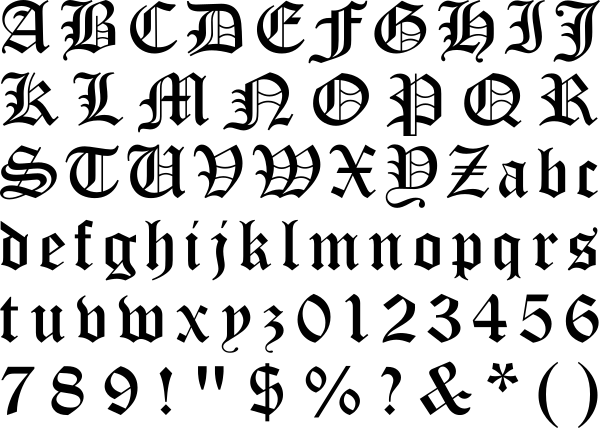
Готический шрифт. Разновидности. (История шрифта, в.Тоотс)
Готическое письмо возникло в 11 в. С начала книгопечатания появились наборные готические шрифты — знаменитая Библия Гутенберга была набрана вариантом текстуры. Само название (от «варварского» народа готов, в действительности не имевшего никакого отношения к этому шрифту) было предложено в XV веке деятелями итальянского возрождения, считавшими такие шрифты «варварскими» и противопоставлявшими их древнеримской письменности.
Общий
вид готических символов определяется
использованием в качестве пишущих
приборов гусиных перьев, обрезанных по
диагонали. Пишущая кромка в большинстве
случаев располагается под углом 45° к
базовой линии строки. Буквы расположены
очень плотно, и ширина межштриховых
промежутков близка к ширине штрихов —
это объясняется необходимостью экономии
дорогостоящего пергамента (отсюда
английское название готического письма —
Blackletter). Широко используются лигатуры
и сокращения.
Основные разновидности
готического письма:
Текстура — острое письмо, первая и основная разновидность готического письма. Своё название текстура получила за то, что покрывала страницу равномерно. Характерное отличие шрифтов данного типа — вытянутость букв.;
Фрактура — острое письмо с ломаными очертаниями, поздняя разновидность готического письма, возникшая в XVII-XVIII вв.;
Швабахер или бастарда — ломаное письмо с округлёнными очертаниями некоторых букв, разновидность готического письма, зародился в XV веке. Ломаное письмо с округлёнными очертаниями некоторых букв. Этот шрифт доминировал в Германии с конца XV до середины XVI века. После чего был заменён на фрактуру, но оставался популярным до XX века.
Ротунда или круглоготическое — переходный вид письма от готического к антикве, отличается округлённостью и отсутствием надломов.
Куррент (готический курсив). устаревшая форма
скорописи, существовавшая в Германии
(в других немецкоязычных странах
распространения не получила).
Готический
курсив был создан на основе
позднесредневекового курсива. В начале
XX века в Германии был принят так называемый
«шрифт Зюттерлина» — стандартизованная
форма готического курсива, преподававшаяся
в школах до запрета Мартином Борманом,
от 1 сентября 1941 года.
В
период ренессанса итальянские
художники-гуманисты, а вслед за ними и
художники других стран, попытались
вернуться к искусству античности. В
каллиграфии снова используется
каролингский минускул, который стали
называть гуманистическим минускулом.
Появляется новое письмо – антиква.
Окончатлеьно установилось начертание
букв g,v,w,x,y. Первая наборная антиква
появилась в Италии и Германии во 2-й
половине XV в. и была значительно
усовершенствована в 70-х гг. XV в. Термин
«Антиква» (Antiqua) заимствован из немецкого
языка (где он обозначает любой шрифт
прямого начертания) и указывает на его
древнее (античное) происхождение,
поскольку каролингское письмо VIII–IX
вв., лежащее в основе гуманистического
письма, в эпоху Ренессанса ошибочно
принималось за подлинное письмо
античности.
Антиква старого стиля— название большой группы ранних антиквенных шрифтов конца XV–нач. XVIII вв., форма которых определялась дуктальным принципом и опиралась на письмо итальянских гуманистов эпохи Ренессанс. Это малоконтрастные или среднеконтрастные шрифты, сохраняющие элементы каллиграфии ширококонечным пером: чуть прогнутые засечки, наклонные оси овалов, растянутые каплевидные элементы. По пропорциям знаки старостильной антиквы сильно разноширинны. Отношение очка строчных и прописных знаков определяется золотым сечением.
Антиква
нового стиля-Собирательное название
группы контрастных шрифтов с тонкими
нескругленными засечками, строго
вертикальными осями овалов, близкими
по форме к окружности каплевидными
элементами. Пропорции знаков стремятся
к одноширинности. Антиква нового стиля
была разработана в конце XVIII в. типографом
и пуансонистом Фирменом Дидо (1764–1836)
во Франции, Джамбаттиста Бодони
(1740–1813) в Италии и Юстусом Эрихом
Вальбаумом (1768–1839) в Германии и широко
применялась до 1-й трети ХIХ в.
Переходная антиква
Готи́ческое письмо́ — семейство почерков латинского письма эпохи Средневековья. Было распространено в ряде европейских стран с середины XII до XVII века.
Латинская Библия (1407, Англия)Страница нидерландско-немецкого словаря (1759). Нидерландский текст набран антиквой, а немецкий — готическим шрифтом- О письме готского языка см. готское письмо
С началом книгопечатания появились наборные готические шрифты — знаменитая Библия Гутенберга была набрана вариантом текстуры. В Италии первые печатные книги с готическим шрифтом появились в 1473 году (это были сочинения Хуана де Торквемады и Роберто Караччоло)[1].